プリキュアのフォント2019(PDF版)
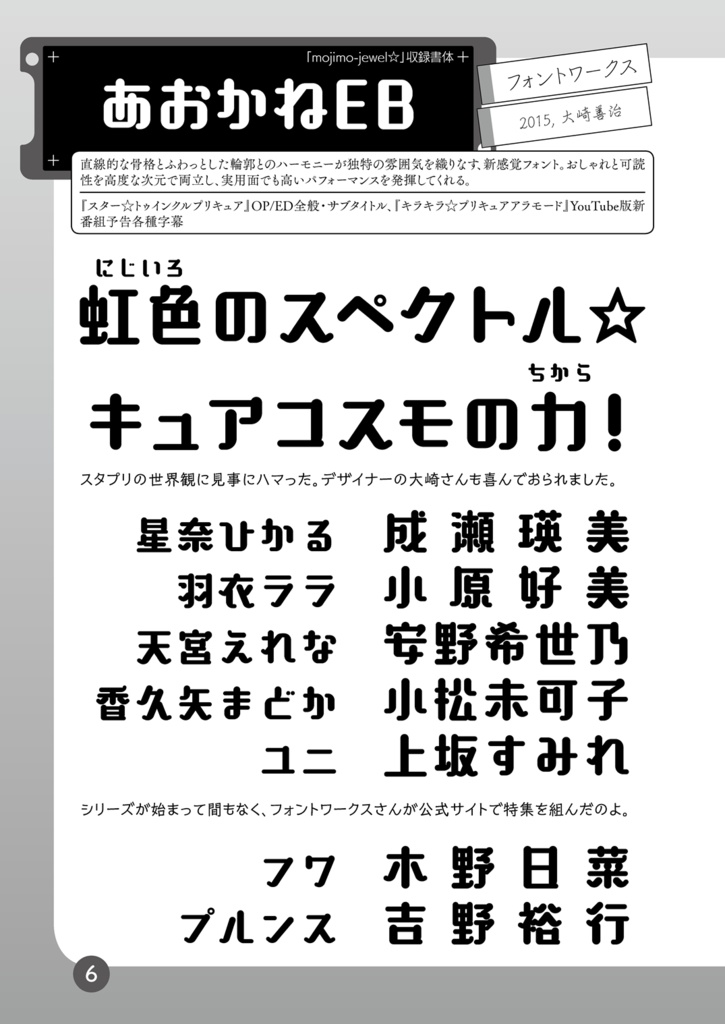
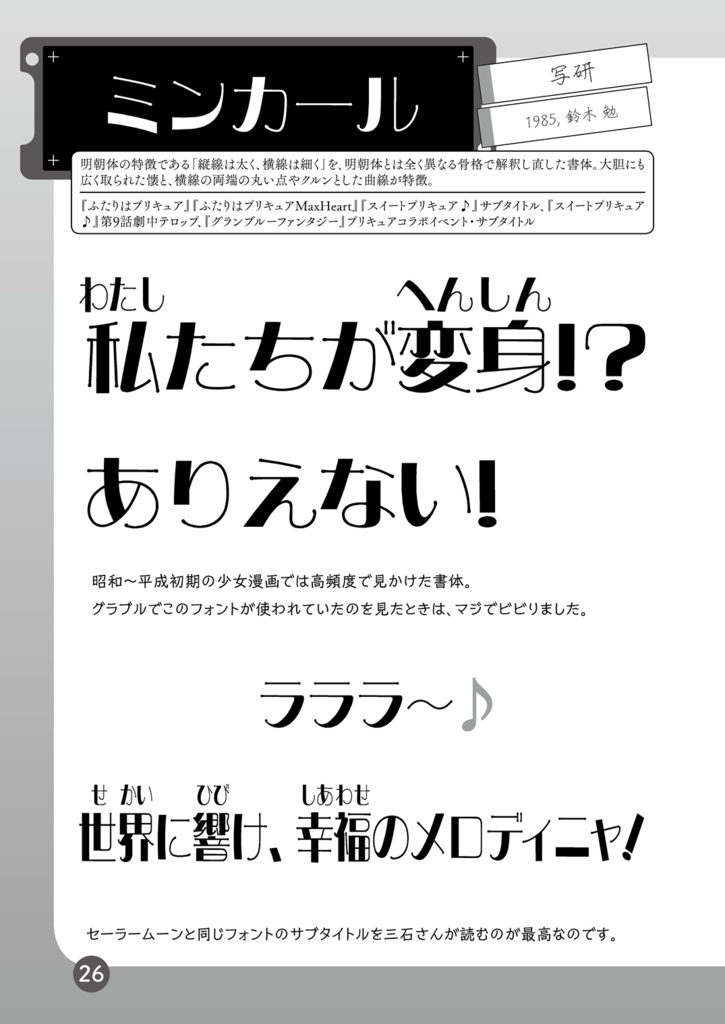
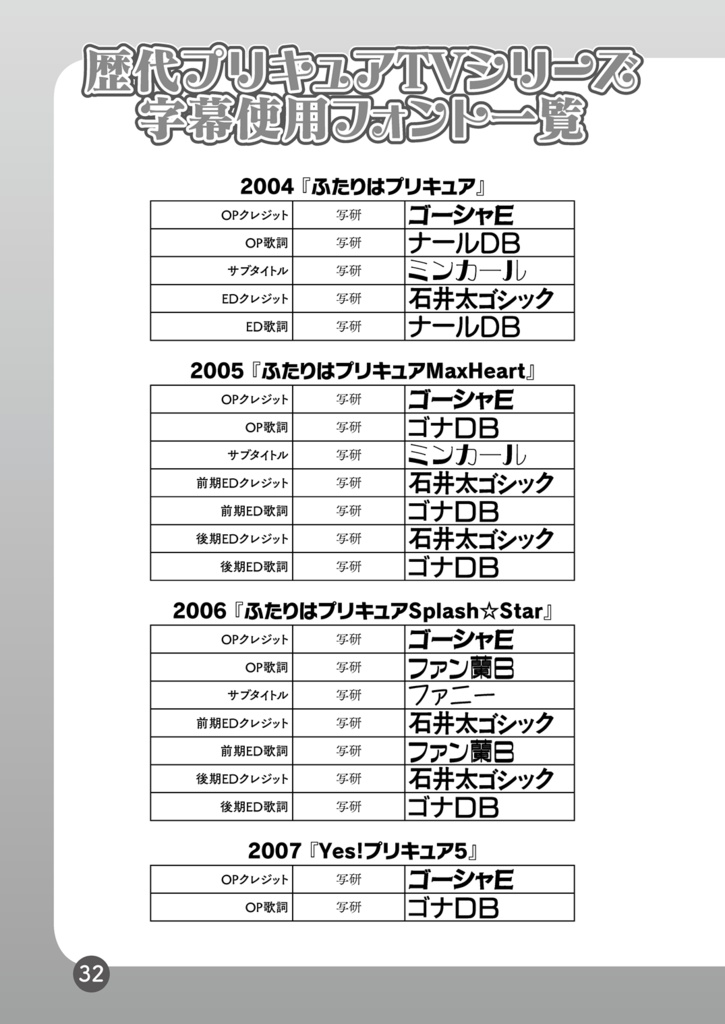
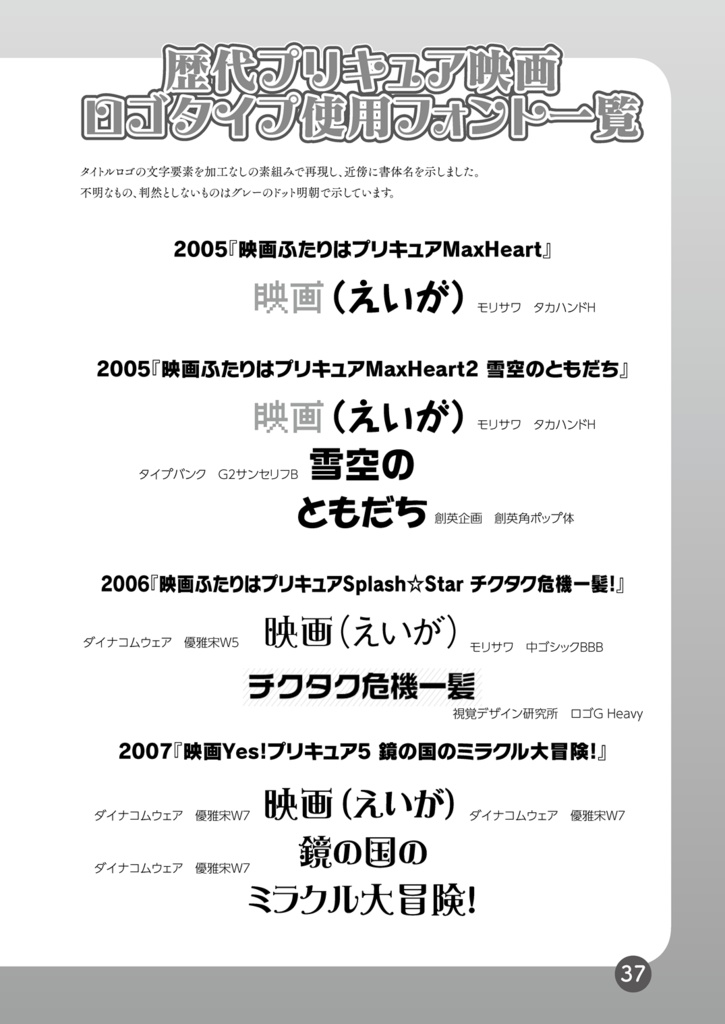
歴代プリキュアのTVシリーズや映画などで使用されてきたフォントの数々を紹介する「プリキュアのフォント」2019年版。 プリキュア16年(当時)の歴史をフォントで振り返っています。TVシリーズで使用された写研やフォントワークスのほか、プリキュアに縁のあるフォントを集めてみました。 今回はフォントワークスさんからプリキュアフォント入門編としても最適な「mojimo-jewel☆」がリリースされた(当時)ことを受け、その収録書体を中心に解説を増やしています。 ※本書に掲載の情報は全て、本書がオフセット本として製作された2019年9月のものです。
プリキュア書体紹介
TVシリーズから劇場版、関連商品に至るまで、プリキュアに縁の深い書体を組見本で紹介しています。見慣れてはいるけど知らなかった書体の名前、わかるかも知れません。
歴代プリキュアTVシリーズ字幕使用フォント一覧
2004年の『ふたりはプリキュア』から2019年の『スター☆トゥインクルプリキュア』まで、オープニングやエンディング、サブタイトルで使用された字幕フォントの一覧です。
歴代プリキュア映画ロゴタイプ使用フォント一覧
2005年の劇場第1作『映画ふたりはプリキュアMaxHeart』から2019年の第27作『映画スター☆トゥインクルプリキュア 星のうたに想いをこめて』までの映画ロゴタイプで使用されたフォントを、併映作品まで含めて判明した限り紹介しています。